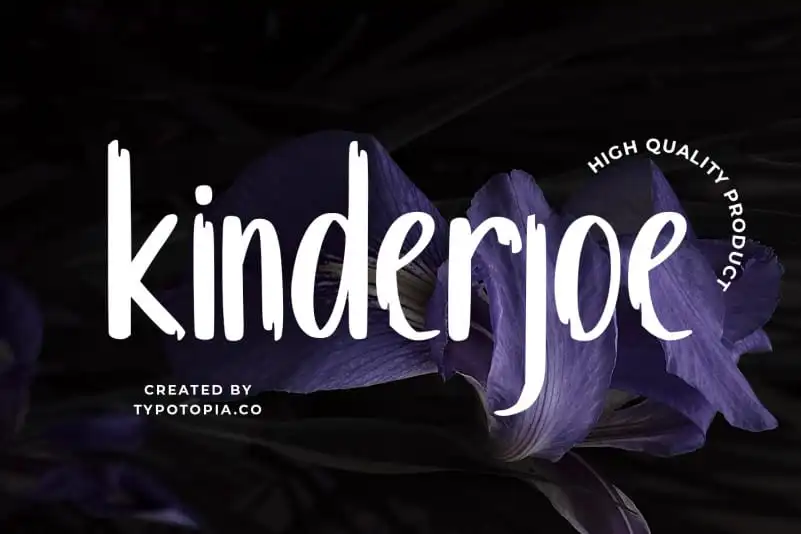
Kinderjoe Display Font – Fonte Grátis
Kinderjoe Display Font
Introduzimos Kinderjoe Display Font, uma exótica e interessante fonte de display que certamente vai deixar seu design mais atraente. Este tipo de letra é ideal para criações que buscam destacar-se, seja na sua identidade visual corporativa ou em elementos gráficos como logotipos e publicações digitais. Com suas formas fluidas e cores vibrantes, Kinderjoe Display Font oferece um toque único e criativo, tornando seu projeto ainda mais memorável. Seja você uma agência de design ou um designer independente, este tipo de letra é certamente o complemento perfeito para sua coleção de recursos gráficos. Escolha Kinderjoe Display Font e enriqueça a paleta visual de seus projetos!